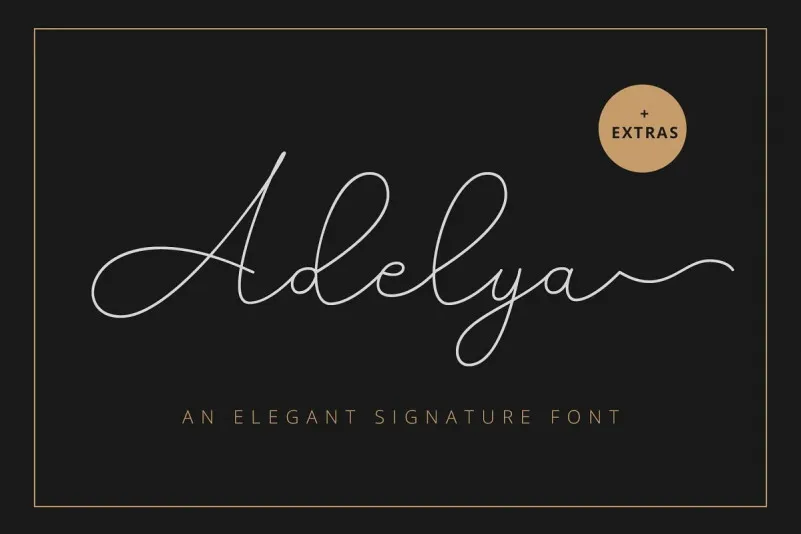
Adelya Font – Fonte Grátis
Adelya Font
A fonte Adelya é uma tipografia monoline com estilo de traçado à mão assinatura, projetada pela Craft Supply Co. Esta tipografia elegante é perfeita para quem busca um visual atraente e versátil para seus projetos gráficos. Com sua forma sinuosa e detalhes finos, Adelya pode ser usada em uma variedade de materiais impressos, desde cartazes até revistas e embalagens, transformando qualquer projeto em algo ainda mais profissional e atrativo. Perfeita para quem procura um toque criativo que destaque seu trabalho, a Adelya é ideal para criar designs impressionantes e memoráveis. Com apenas alguns poucos cliques de ferramentas gráficas adicionais, suas criações se tornarão ainda mais vivas e belas do que nunca. O uso desta fonte certamente dará um toque personalizado à sua próxima obra de arte gráfica.